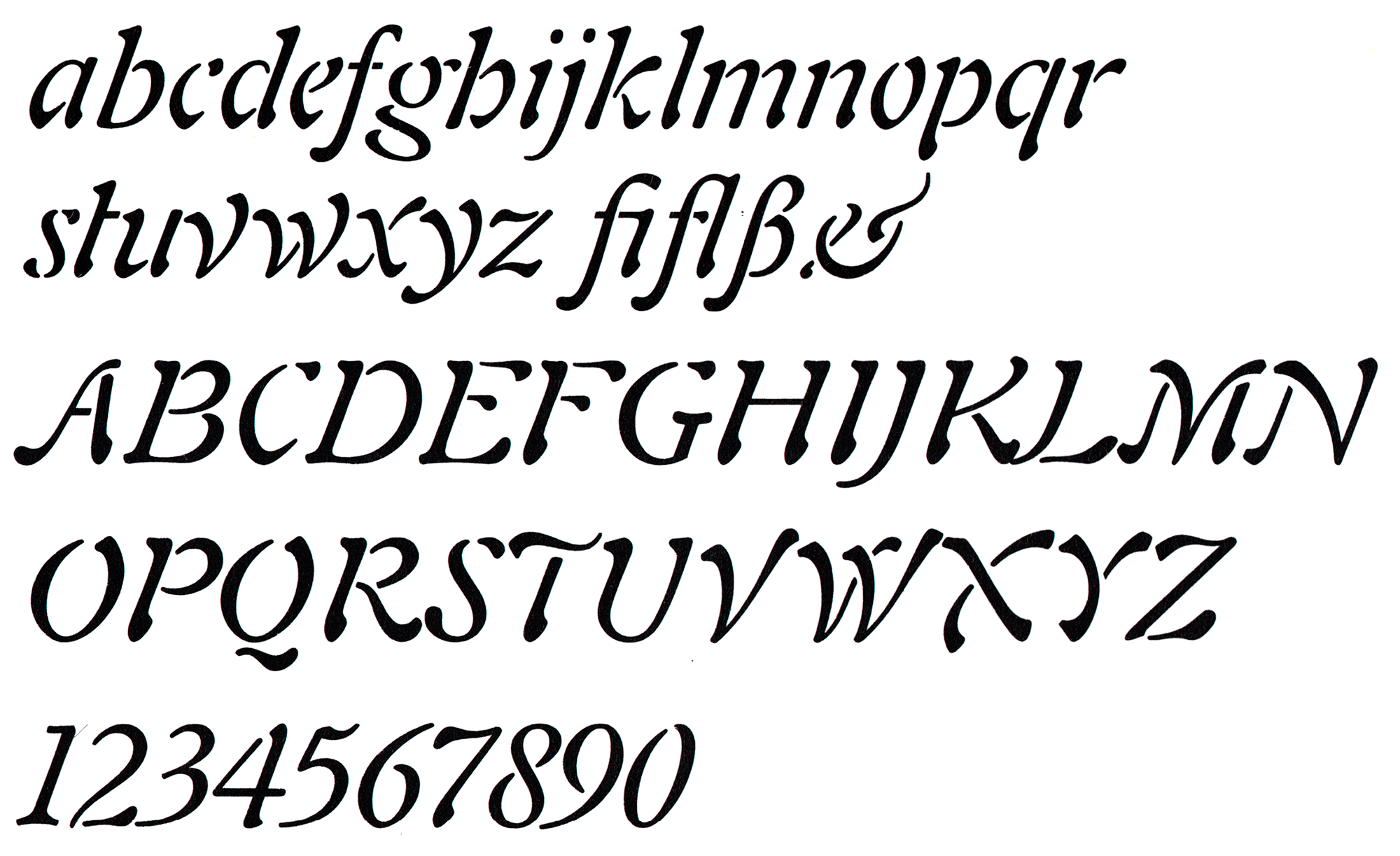
Die Auriol von George Auriol erschien ab 1901 bei Peignot. Die aktuell erhältliche Linotype-Version wurde von Matthew Carter überarbeitet. Mit ihren drei Strichstärken und den zugehörigen Ornament-Fonts gehört sie zu den am besten ausgebauten, digital verfügbaren Jugendstil-Schriften.